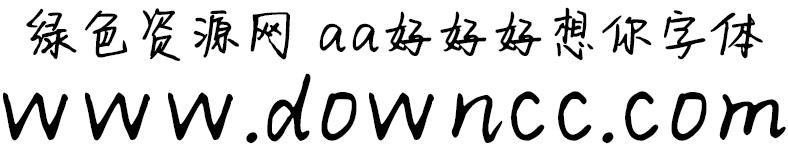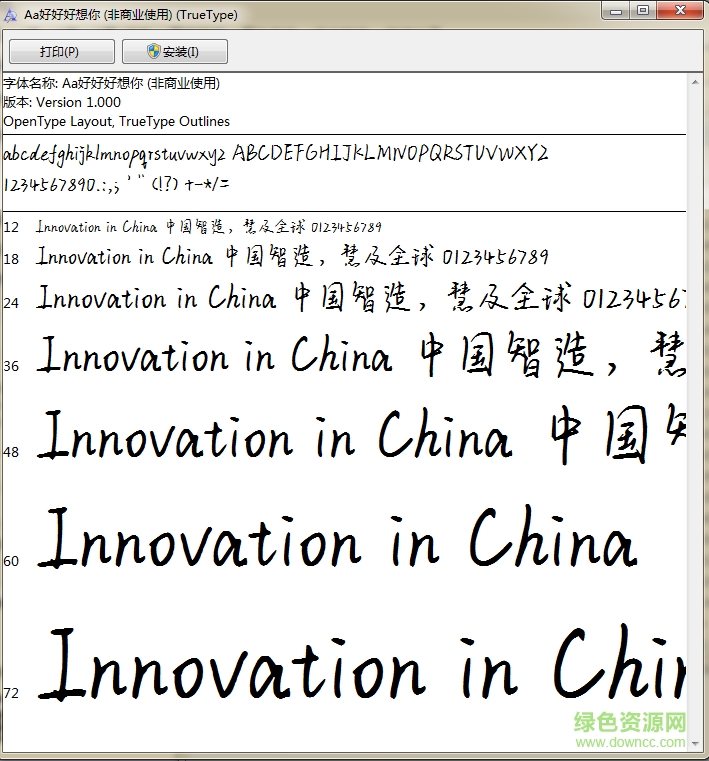
aa好好好想你字體ttf整體字形感覺十分精美,每一個都擁有無窮的情感在里面,讓人感受到濃厚的想念味道,從而能夠帶給用戶不錯的字體使用體驗呢,快來綠色資源網下載吧!
斷指法
把一些封合包圍的字,適當?shù)臄嚅_一口出來 , 或把左邊斷一截,或右邊去一截, 重點:要在能識別的情況下適當斷肢,從而反射他的與眾不同的特點來。